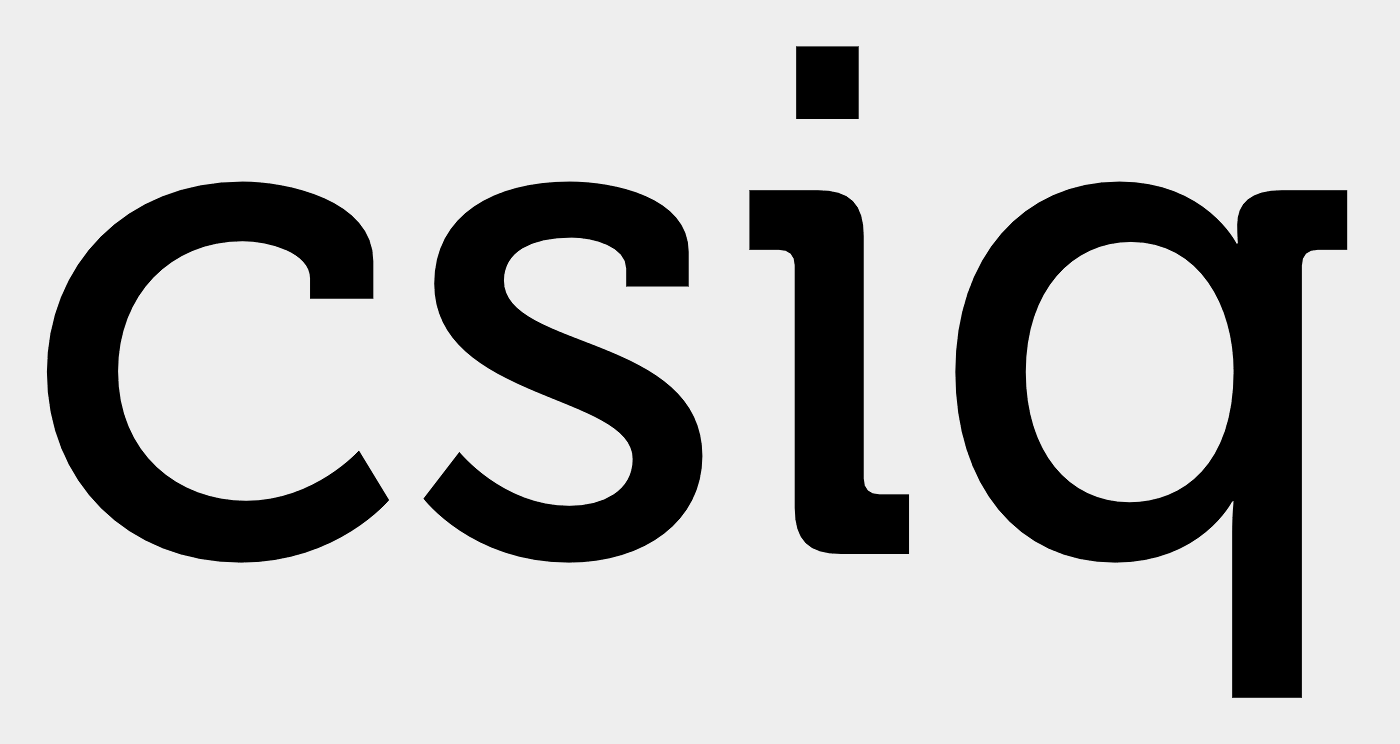
Font mit sehr markantem kleinen "i"
suche für Recherchezwecke den Fontnamen einer Slab-Schrift mit sehr markantem "i", wobei ich nicht sagen kann, ob das "i" evtl. separat designed ist. Es ist für ein Logo und die Ur-Datei ist nicht mehr auffindbar... Kann jemand weiterhelfen? Hier das Bild: font.gif.ab1b6252327cfb56d96cd26672c895f3.gif           -  vielen Dank im voraus.  Gruß, vellvee
csq ist aus der Museo. Das i ist wohl handgemacht.